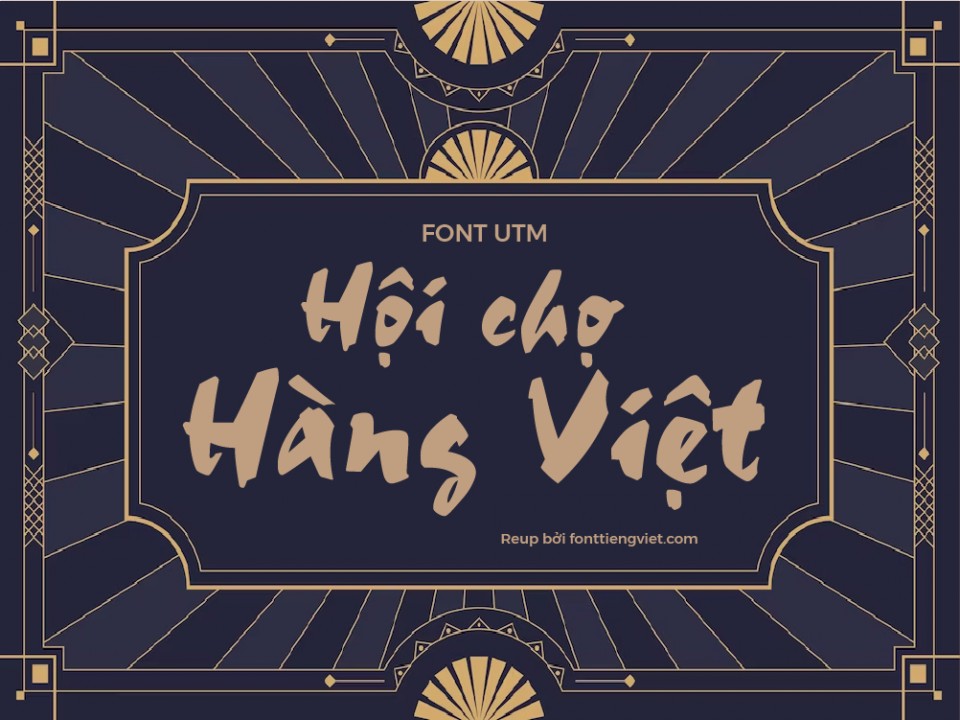
Font việt hóa UTM Staccato
Giới thiệu về bộ Font việt hóa UTM Staccato
Trong thế giới đồ họa hiện đại, việc tìm kiếm một mẫu Font Miễn Phí có phong cách viết tay phóng khoáng là điều vô cùng cần thiết. Font việt hóa UTM Staccato chính là sự lựa chọn hoàn hảo cho những ai yêu thích sự mềm mại nhưng không kém phần mạnh mẽ. Đây là một phông chữ script đầy cá tính, được tinh chỉnh tỉ mỉ để phù hợp với bảng mã tiếng Việt, giúp người dùng dễ dàng ứng dụng vào nhiều loại hình thiết kế khác nhau từ học đường đến chuyên nghiệp.
Đặc điểm nổi bật của font chữ này
UTM Staccato sở hữu những đường nét uốn lượn tự nhiên, tạo cảm giác như được viết trực tiếp bằng bút mực trên giấy. Điểm đặc biệt của Font việt hóa UTM Staccato là sự cân bằng giữa các nét thanh và nét đậm, mang lại hiệu ứng thị giác ấn tượng. Đối với các bạn học sinh và giáo viên, bộ font này cực kỳ hữu ích trong việc thiết kế thiệp mời, làm báo tường hoặc trang trí các tiêu đề bài giảng điện tử sinh động.
Cách ứng dụng Font việt hóa UTM Staccato hiệu quả
Để phát huy tối đa vẻ đẹp của font chữ, bạn nên sử dụng nó cho các đoạn văn bản ngắn hoặc tiêu đề chính. Việc kết hợp Font việt hóa UTM Staccato với các phông chữ không chân (sans-serif) sẽ tạo ra sự tương phản hiện đại và tinh tế. Ngoài ra, hãy chú ý đến khoảng cách giữa các chữ cái để đảm bảo tính dễ đọc khi in ấn trên các sản phẩm như bìa sách hay poster sự kiện nhà trường.